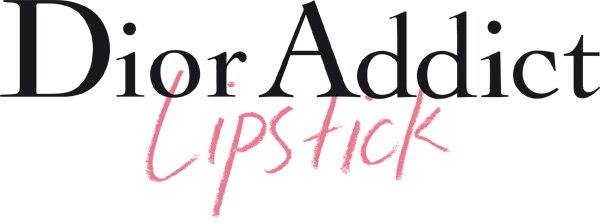
Suche Schrift von neuer Dior Werbekampagne "Dior Addict Lipstick"!
Ich suche die Schrift von der neuen Werbekampagne von Dior!
Die Schrift von "Dior" und "Addict" kenne ich bereits, aber ich rätsel noch, welche Schrift für das "Lispstick" benutzt wurde.
Könnte das evtl. handschriftlich sein?
Hier die Kampagne:
Das sieht handgemalt aus. Zwei verschiedene kleine i in einem Font … ?
Was für ein Font ist denn für den Dior-Schriftzug genutzt worden?
Hmmm, das weiß ich leider nicht, aber als Alternative für die Handschrift könnte die Sammy von Fontsmith geeignet sein. :-)
Die Cochin geht ja in die richtige Richtung, aber die passt doch nicht genau. die (Dach-)Anstricke sind anders, beim r ist der Auslauf in kugeliger Form. Gibt es noch eine passendere Typo?
Ralf schrieb zur Cochin ja auch »nah dran«. ;-)
Ich habe ebenfalls gesucht, aber keine passende Schrift gefunden. Wie es aussieht, ist das ist keine der üblichen Verdächtigen.
hm, genau, die üblichen aus der Klassifikation hab ich mir auch schon angeschaut.
@ Jenita: Ersten glaube ich nicht, dass das die Cochin ist, sondern dass das ein etwas unbekannterer Font ist, den Dior da verwendet hat. Vielleicht ist das sogar die Dior-Hausschrift? Das wäre bei einem so exklusiven Unternehmen ja nicht ganz abwegig.
Dafür stimmen andere Details aber nicht überein.
Die meisten sogar :-) Da werden wohl beide Varianten bei der Logogestaltung Pate gestanden haben.
In ihrer Kommunikation verwendet Dior die Cochin LT, das Logo ist immer als Logo eingebunden, nie als Schrift.